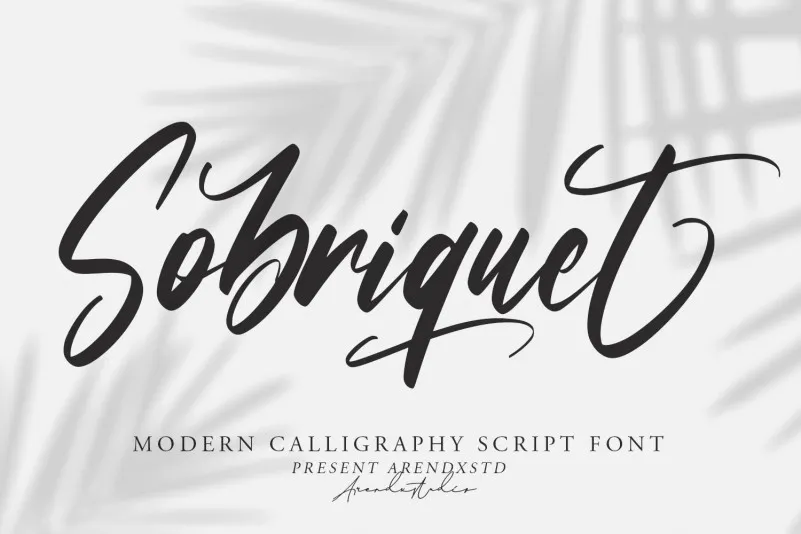
Sobriquet Font – Download Grátis
A Sobriquet Font é uma delicada e elegante escrita à mão que foram criadas pela Arendxstudio, repleta de caracteres bonitos, alternativas únicas e ligaturas sofisticadas. Esta fonte Calligrafia é relaxada e flui sem esforço. Com sua versatilidade incrível, ela se adapta a uma ampla gama de ideias criativas, elevando-as ao nível mais alto. Adicione esta font à sua coleção favorita de ideias criativas e observe como ela as torna vivas e reais. A Sobriquet é perfeita para aqueles que desejam dar um toque sofisticado a seus designs, seja em logotipos, cartões de visita ou qualquer outro projeto visual.